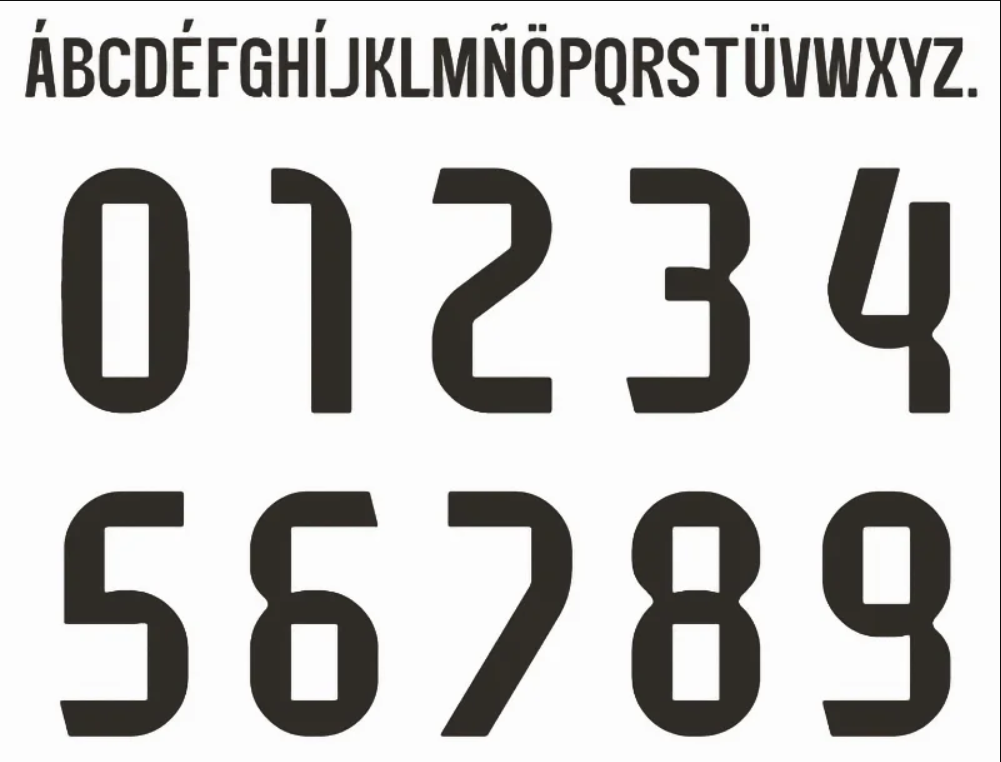
Fonte Real Madrid 2025/2026 – Download TTF e Vetor para Personalização
Fonte Real Madrid 2025/2026 (Adidas) – Download TTF e Vetor para Personalização
Quando falamos do Real Madrid, falamos de realeza, história e da camisa mais pesada do futebol mundial. Para a temporada 2025-2026, a parceria com a Adidas trouxe mais uma vez um kit que impõe respeito nos gramados da La Liga e da Champions League.
Se você trabalha com personalização de camisas ou design esportivo, ter a tipografia correta dos “Merengues” é obrigatório. Neste post, trazemos o arquivo da fonte oficial para que você possa reproduzir os nomes de craques como Vini Jr, Bellingham e Mbappé com perfeição.
• Conteúdo: Alfabeto completo (A-Z), numeração oficial (0-9) e caracteres especiais.
Estilo Visual e Identidade
A tipografia criada pela Adidas para o clube espanhol nesta temporada aposta em um visual moderno, mas sem perder a classe clássica do clube.
O estilo apresenta traços sólidos e levemente condensados, garantindo excelente legibilidade à distância. Diferente de fontes anteriores que apostavam em serifas ou cortes agressivos, a versão 2025/26 foca na elegância minimalista, harmonizando perfeitamente com o branco tradicional do uniforme titular e com as cores ousadas dos uniformes 2 (Away) e 3 (Third). É a fonte ideal para dar um acabamento premium a qualquer mockup ou réplica.